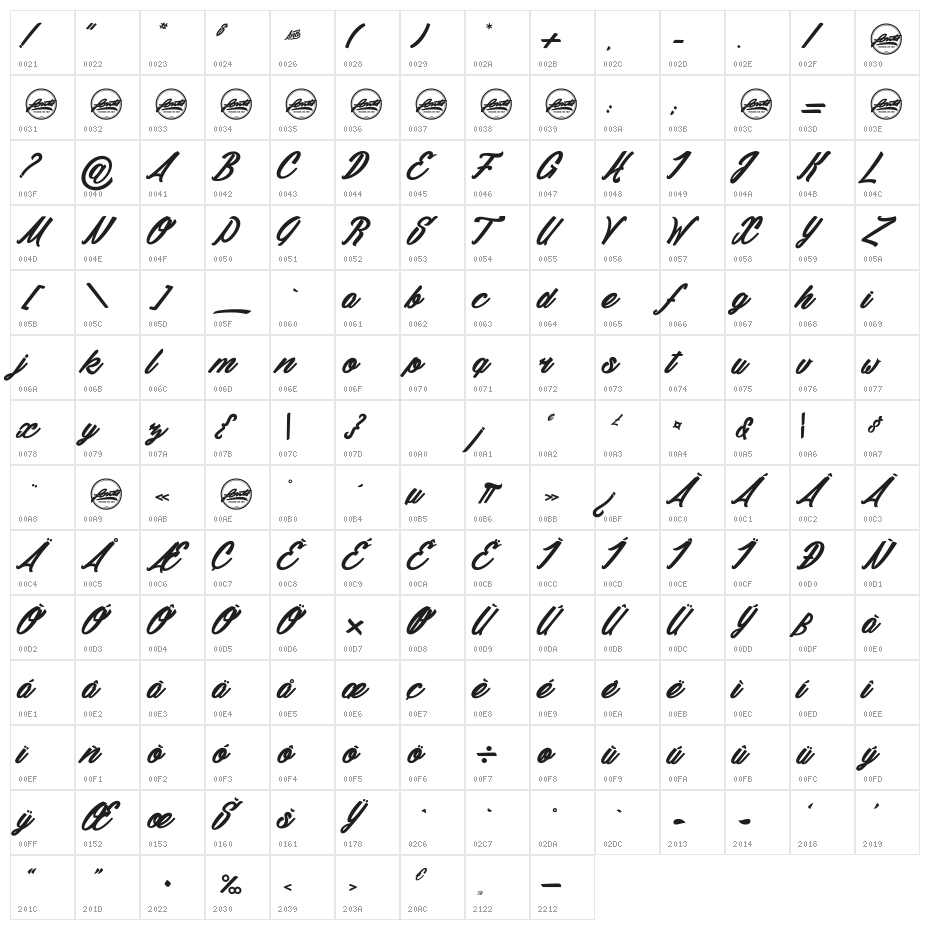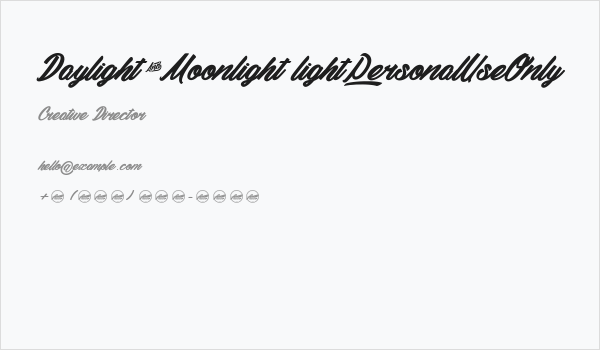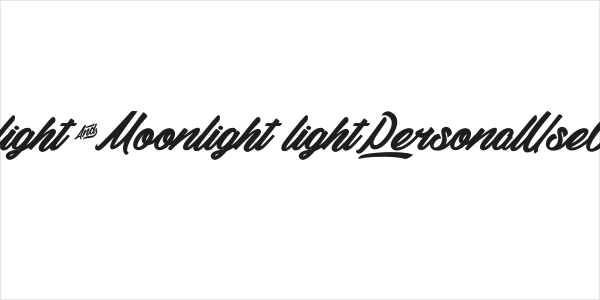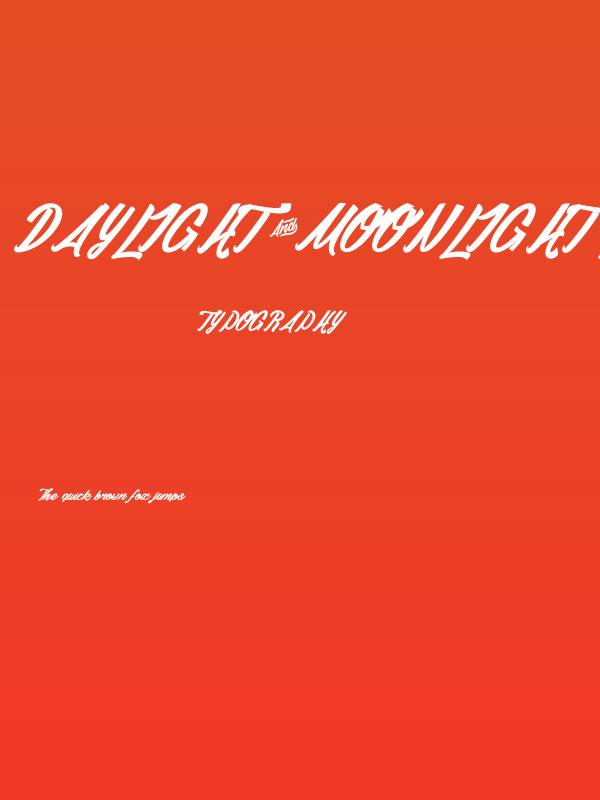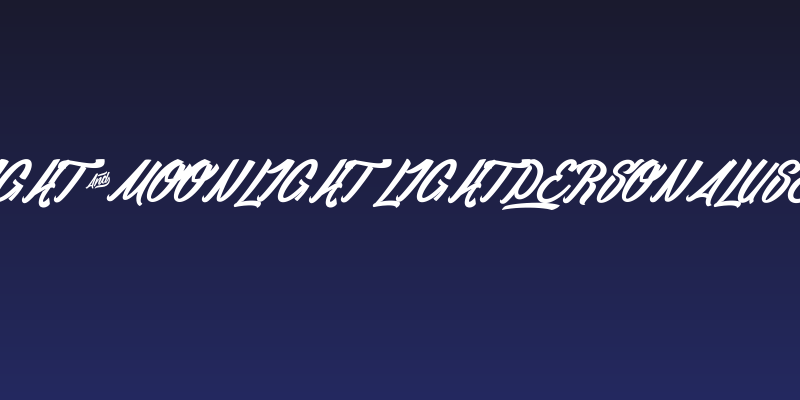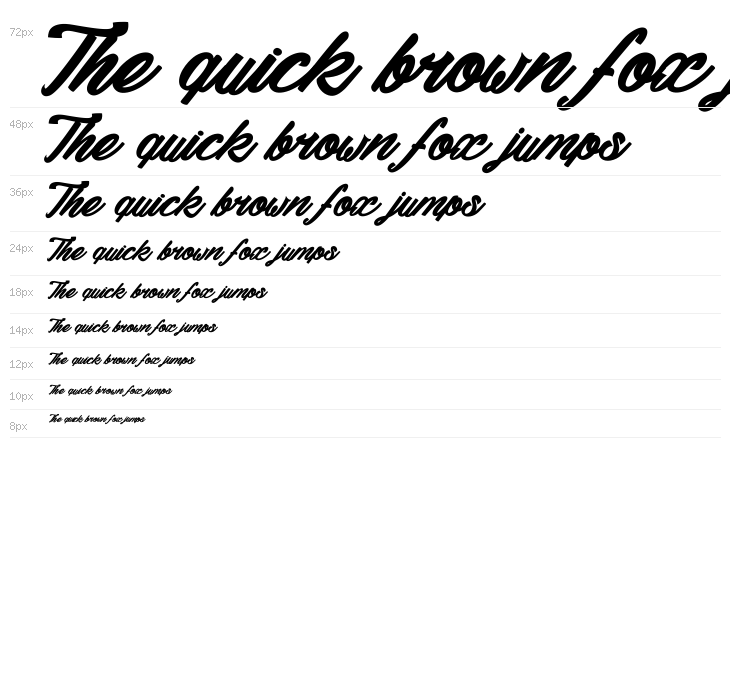
Daylight&Moonlight light_PersonalUseOnly Font
✎ Script
| Categorias | Script |
| Caso de uso | Logos, Headlines, Invitations |
| Projetos propostos | Ideal for branding, logos, invitations, and headlines where a stylish, personal touch is desired. |